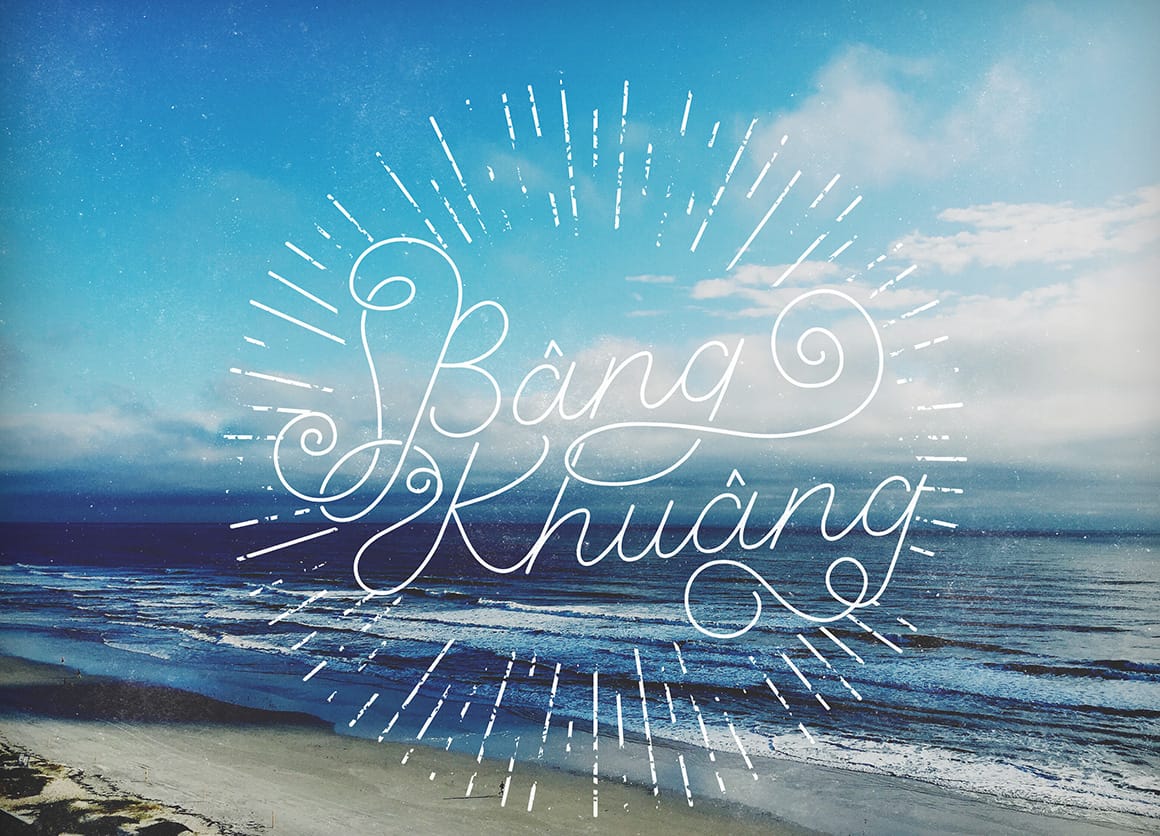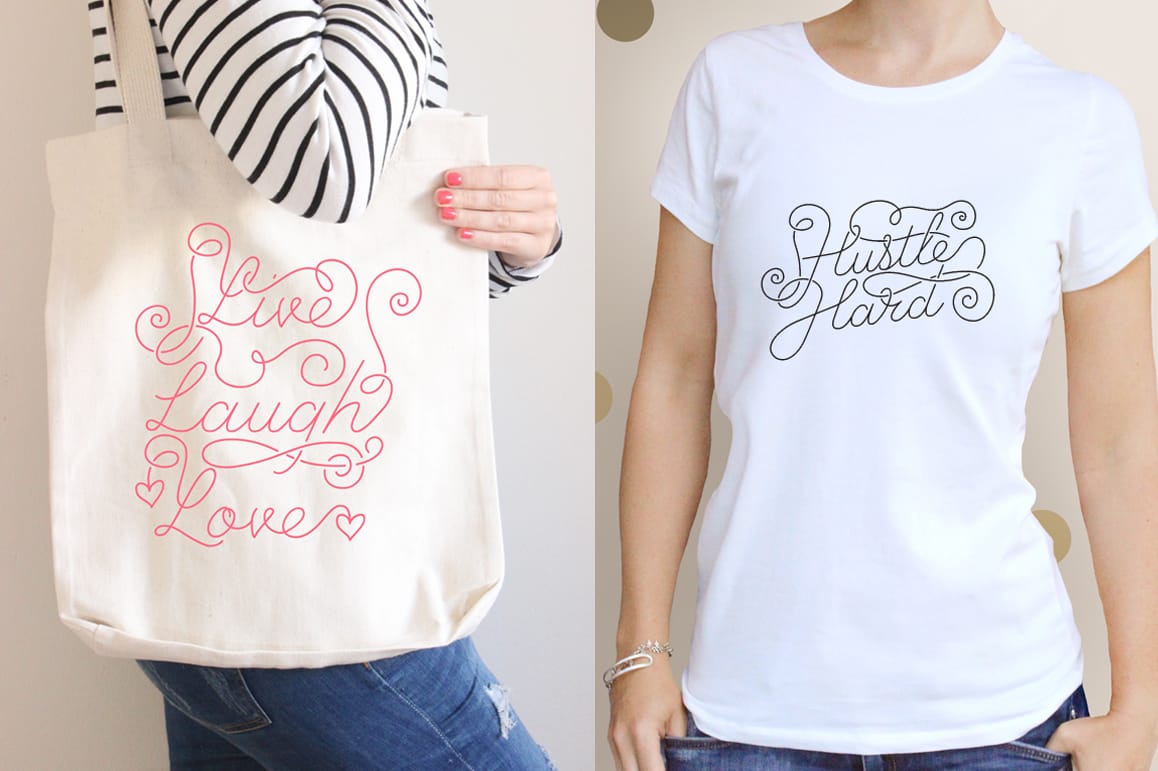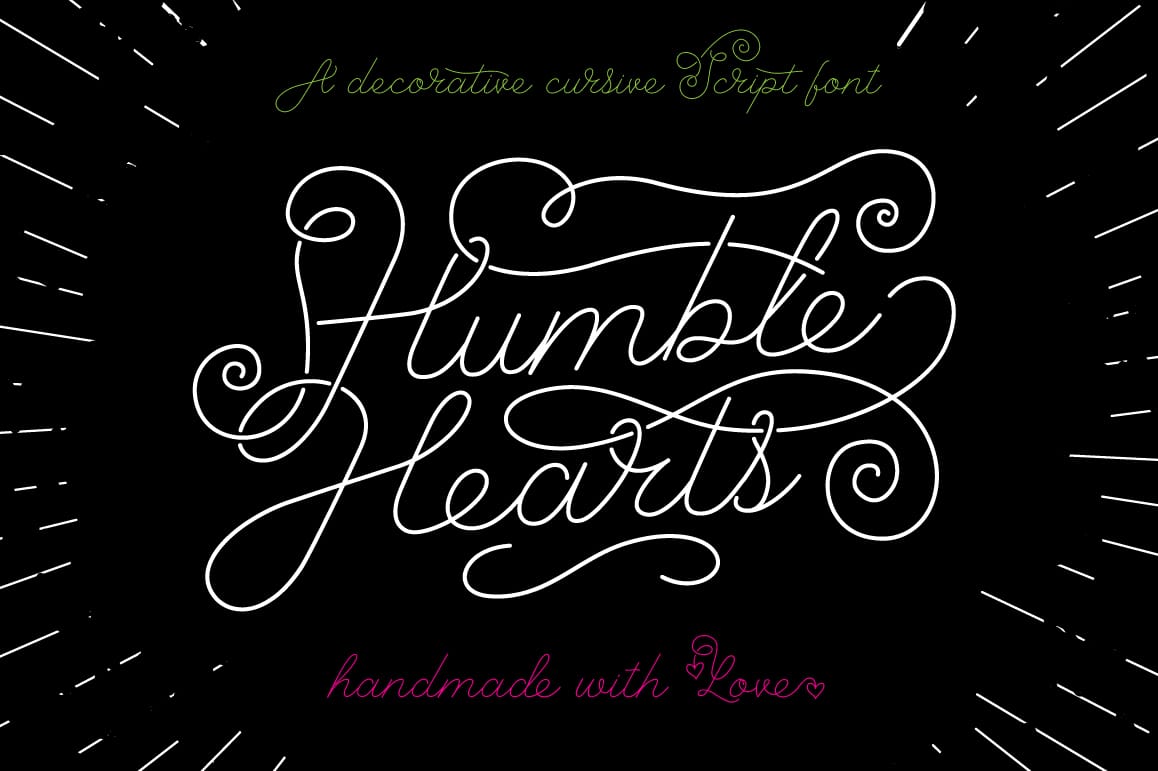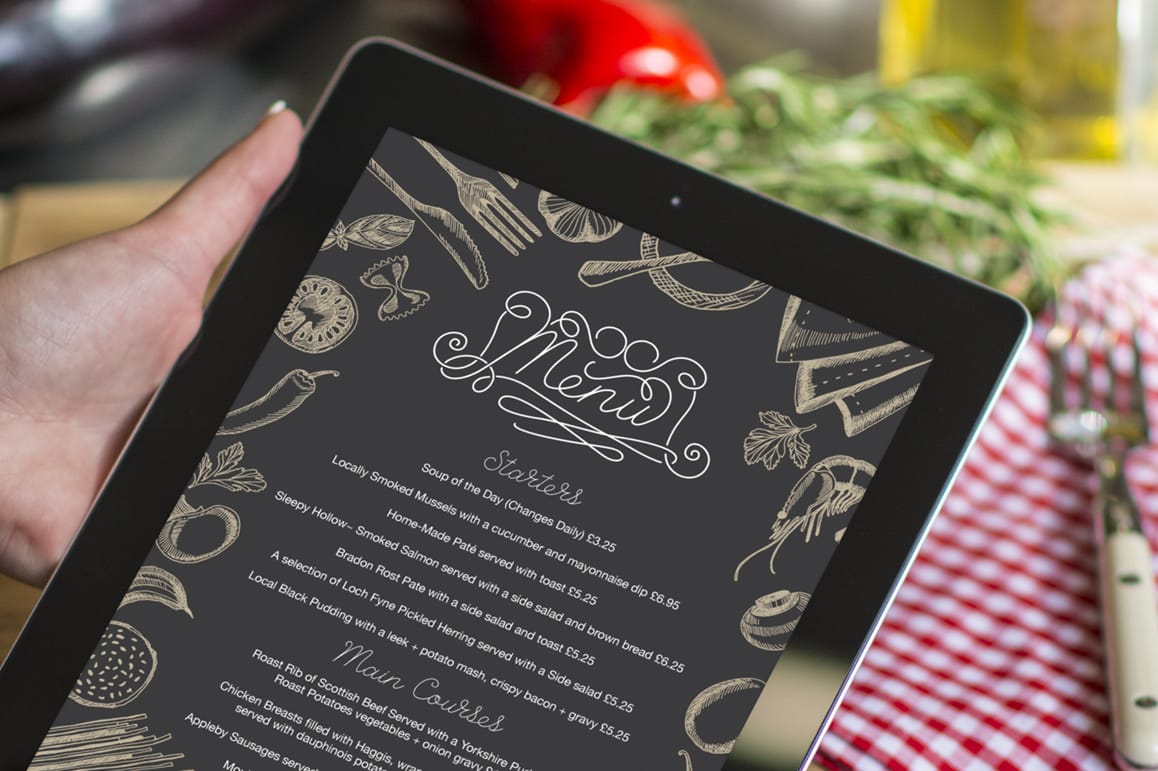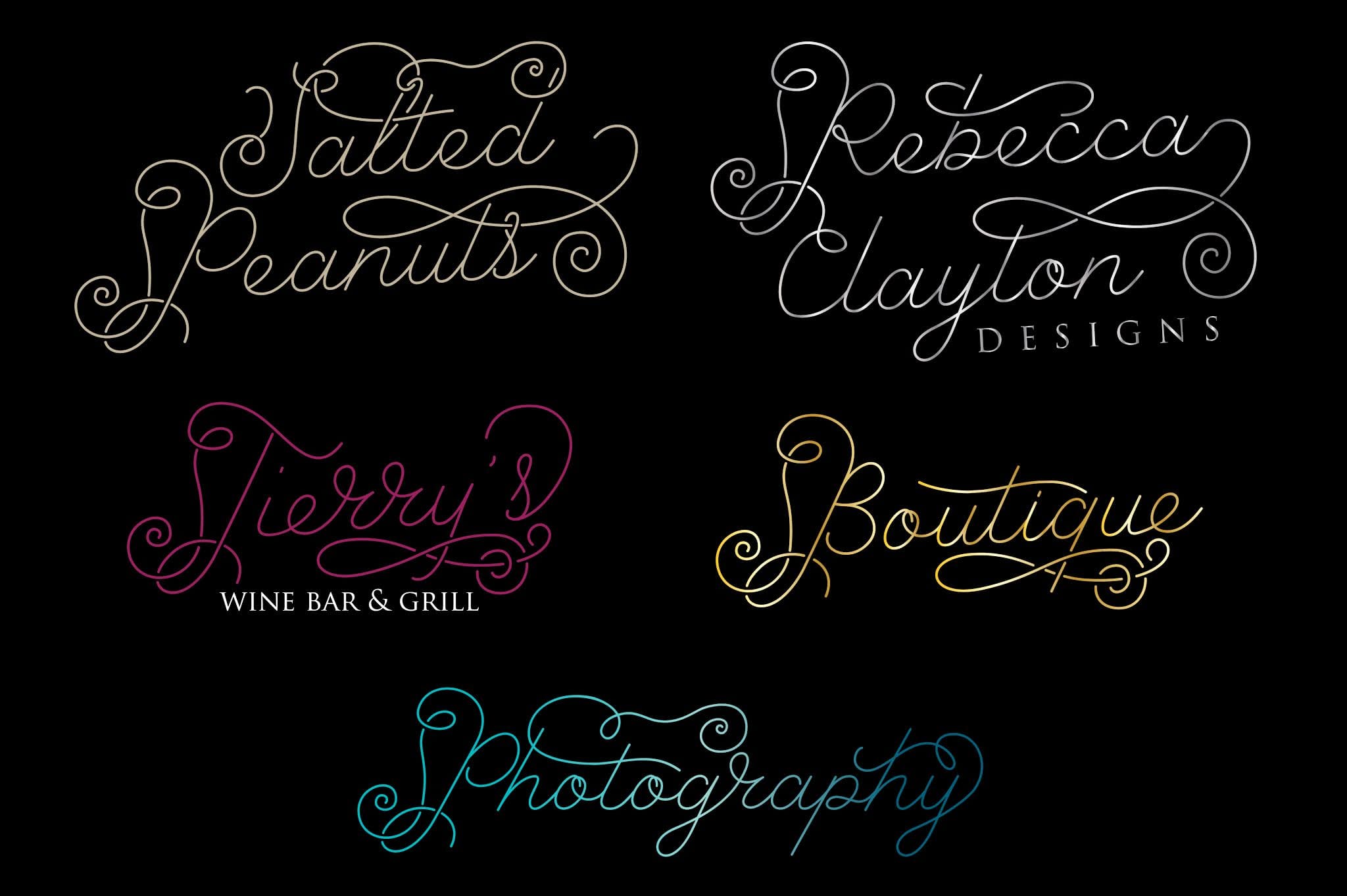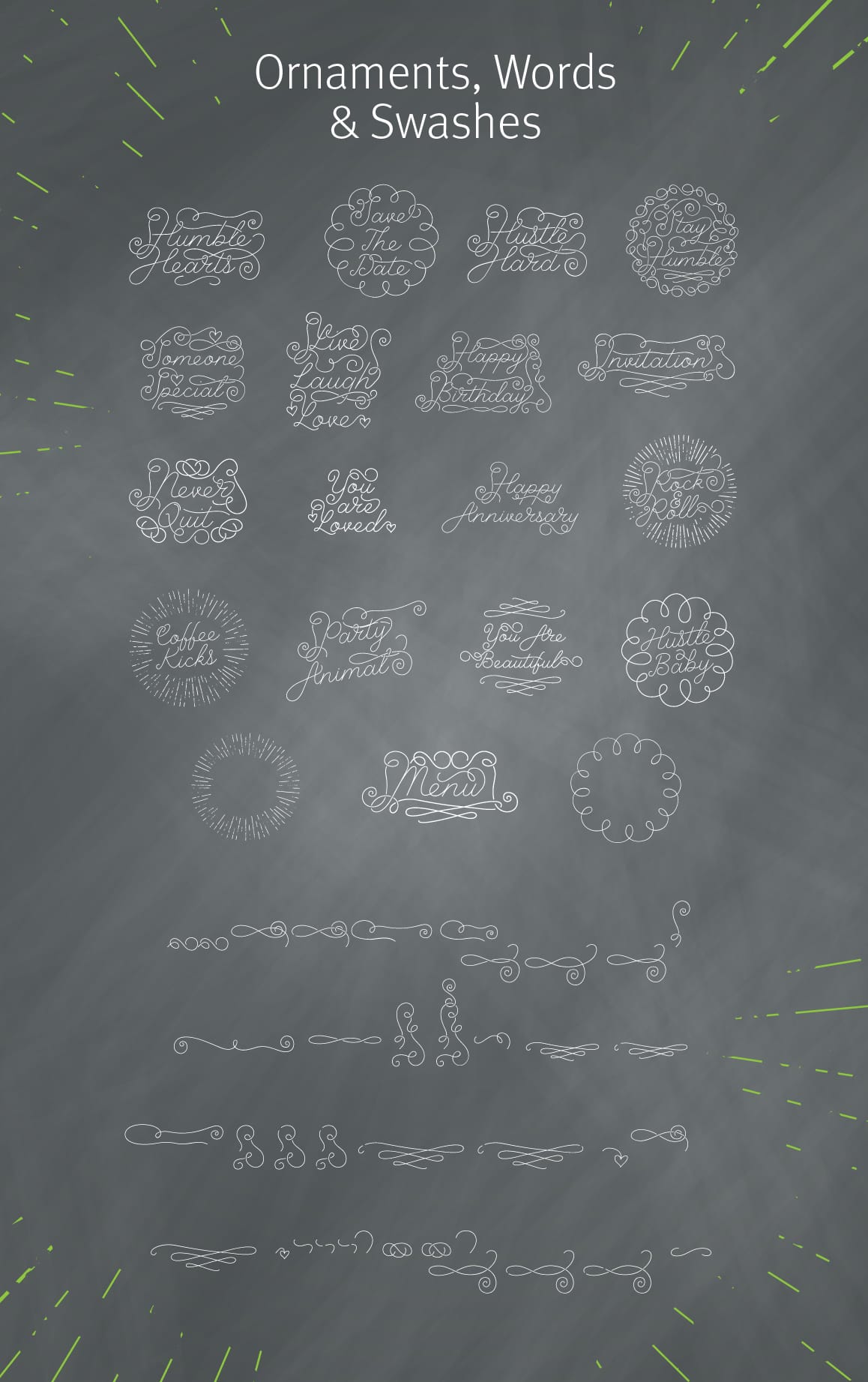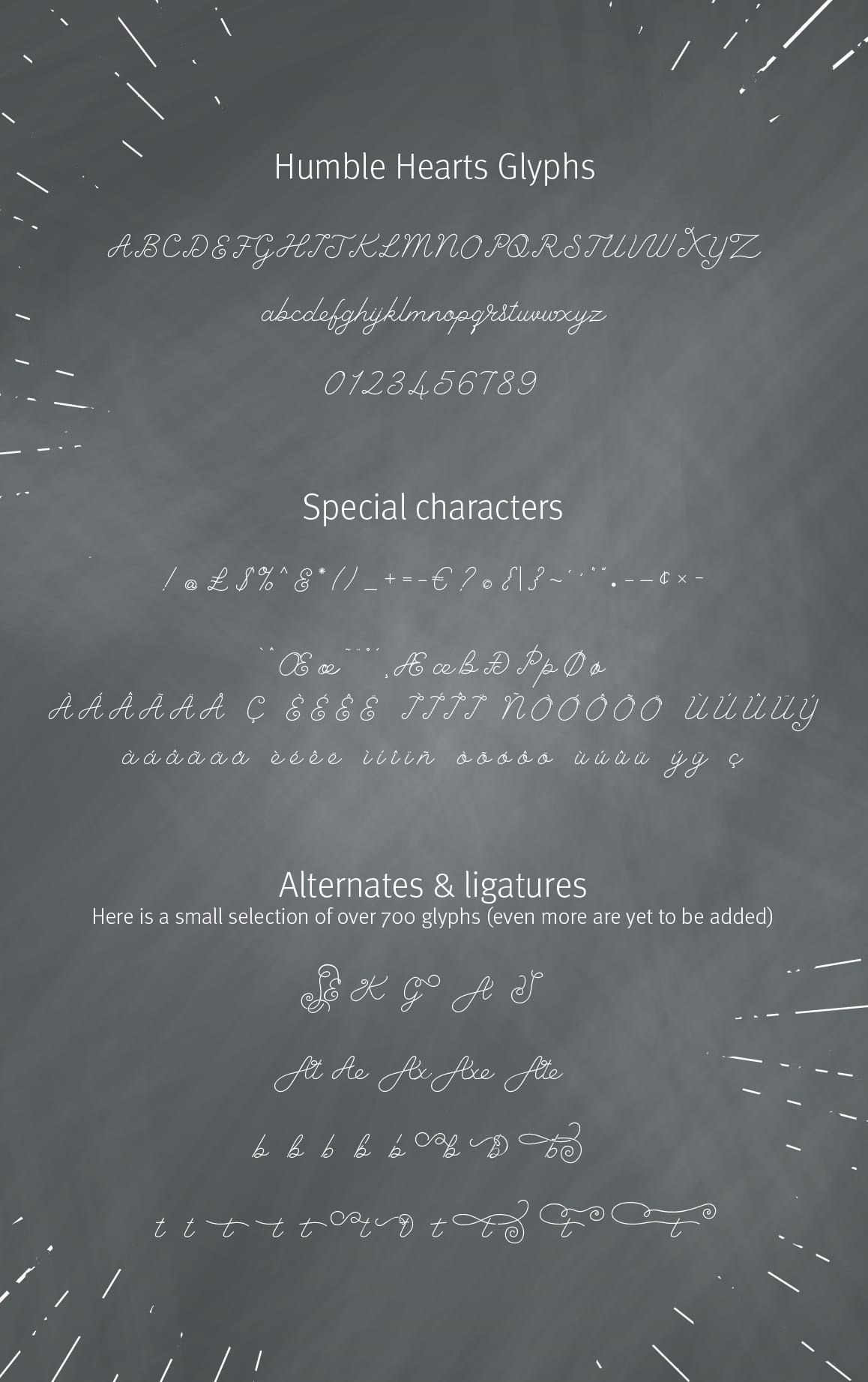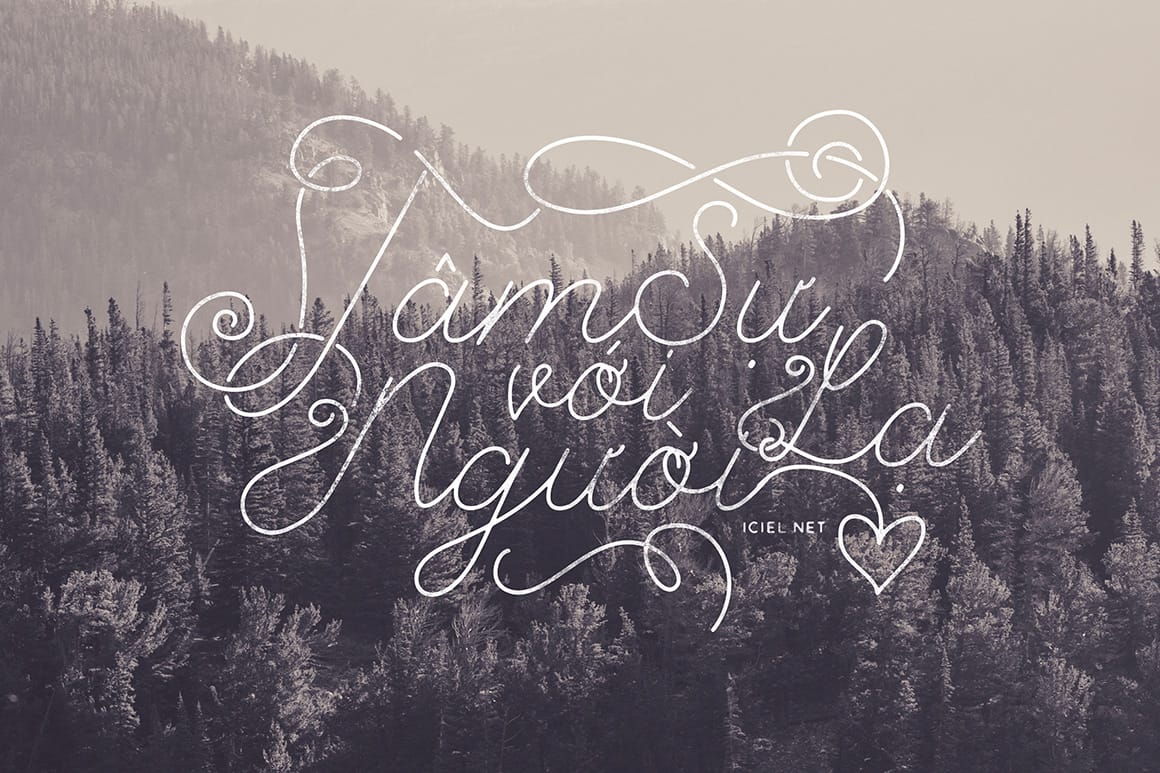
Font Humble Hearts việt hóa bởi iCiel là một font viết tay monoline, được thiết kế độc đáo và cầu kì, mang không khí hand lettering đơn giản nhưng vẫn vô cùng thân thiện. Với hơn 750 kí tự, bạn có thể tha hồ sáng tạo với font. Phù hợp dùng trong các tác phẩm in ấn, logo, áo phông, thiệp cưới, v..v..